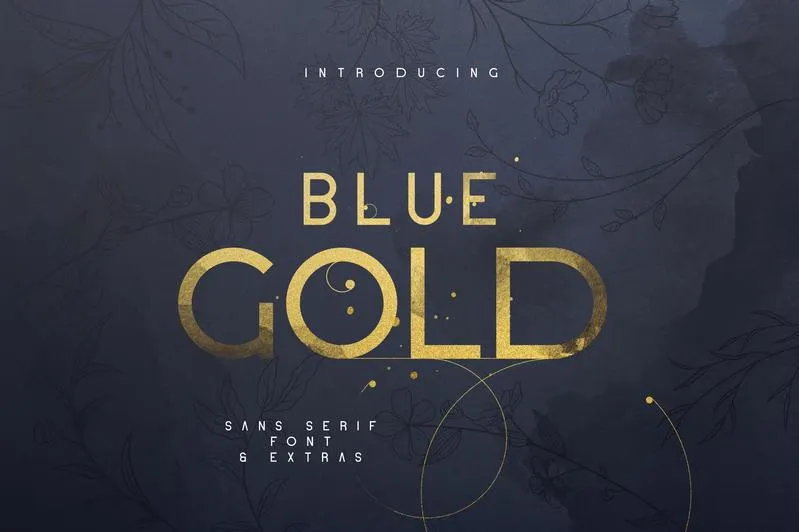
Blue Gold Sans Serif Font + Extras – Download Grátis
A Blue Gold Sans Serif Font + Extras é uma escolha perfeita para quem procura uma fonte limpa e versátil. Esta fonte está na caixa de todos os requisitos, com tons de alternativas gílias, ornamentos, elementos naturais como águacolorismo e marcadores em tinta, tudo no idioma padrão suportado. Ela não só oferece um formato todo maiúsculo que dá uma sensação alegre e moderna, mas também possui oito estilos de Photoshop e tons de água coloridas para você personalizar e ajustar conforme necessário. Ideal tanto para textos grandes quanto menores, esta fonte é extremamente versátil. Perfeita para adicionar um toque único em suas criações digitais, seja ela na web ou impressa. Além disso, a multilíngue do produto permite que você utilize a fonte em qualquer idioma desejado. Não importa se o seu próximo projeto é um site de notícias global, uma marca de luxo para seus clientes altamente qualificados ou até mesmo uma coleção de arte digital exclusiva — esta fonte está aqui para complementá-lo. A Blue Gold Sans Serif Font + Extras não apenas oferece um design sólido e moderno, mas também adiciona um toque especial a seu projeto. Com esses extras inclusos, ela se torna definitivamente uma escolha inteligente para qualquer designer que deseja criar algo único e personalizado.